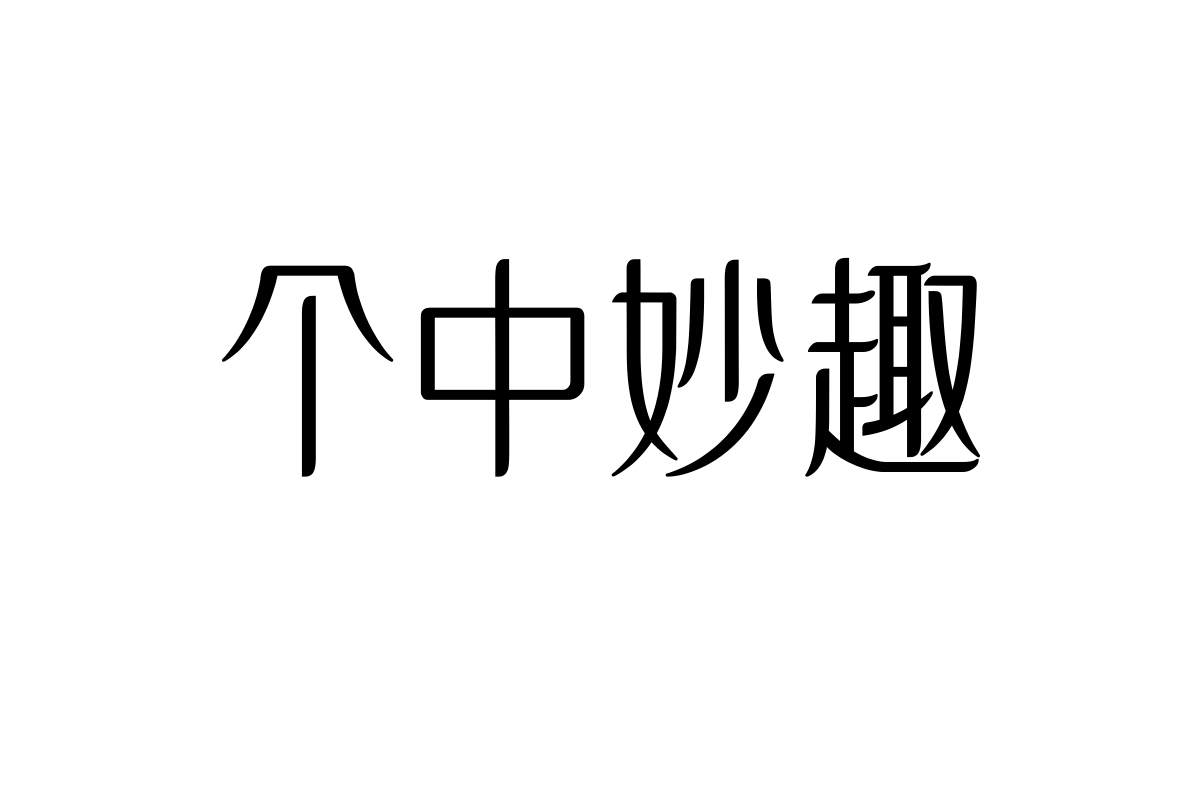
上首倾城体是一种字体,它的设计风格独特,笔画流畅,给人一种优雅的感觉。这种字体的特点是笔画粗细变化明显,线条流畅自然,给人一种优雅的感觉。同时,上首倾城体也具有一定的艺术感,适合用于需要表现艺术感的场合。
上首倾城体的笔画结构复杂,线条流畅自然,给人一种优雅的感觉。这种字体的特点是笔画粗细变化明显,线条流畅自然,给人一种优雅的感觉。同时,上首倾城体也具有一定的艺术感,适合用于需要表现艺术感的场合。
总的来说,上首倾城体是一种非常独特的字体,它的设计风格独特,笔画流畅,给人一种优雅的感觉。这种字体的特点是笔画粗细变化明显,线条流畅自然,给人一种优雅的感觉。同时,上首倾城体也具有一定的艺术感,适合用于需要表现艺术感的场合。